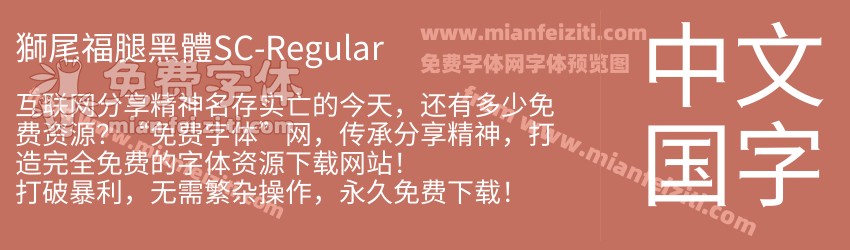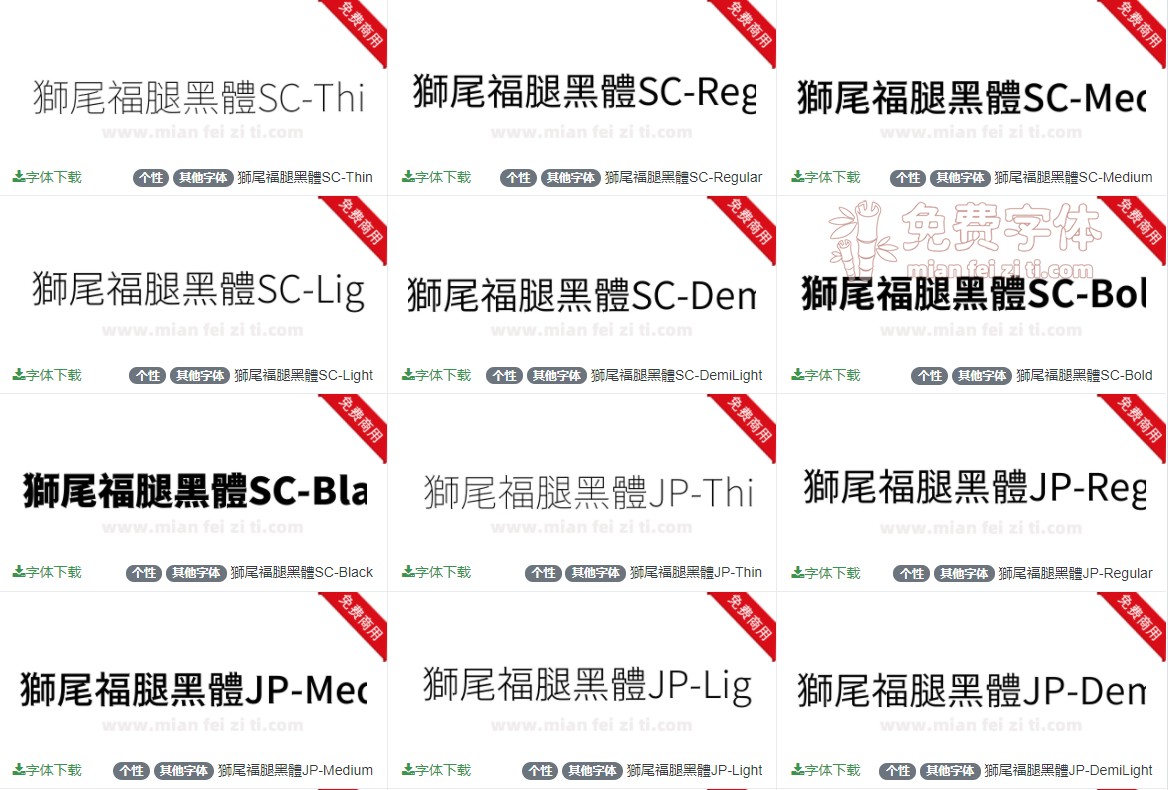
狮尾福腿黑体基于思源黑体的笔触增加三角形改造,更加简明现代化的字体。支援简体中文、繁体中文、韩文与日文;可以免费商用,欢迎大家自由应用、自由优化、自由改作!
狮尾福腿黑体的特色是,「一」字的开头和结尾笔触由平头增加一个小小的三角形。
「狮尾福腿黑体」与「狮尾福音黑体」差别在有没有拔脚,「拔脚」就是会有较少的笔画,例如移除「口」字的左右下角会多出的短线条。有拔脚的字会较圆,但是会造成有些字因直接去掉腿后左右不平衡、左右不对衬的「悬空」问题。改使用「腿」系列字体就不会有这个问题。
• SC是 Simplified Chinese 简体中文,代表大陆习惯字形。
• TC是 Traditional Chinese 繁体中文,代表港台习惯的字形。
• JP是 Japanese 日文,代表日本习惯字形。